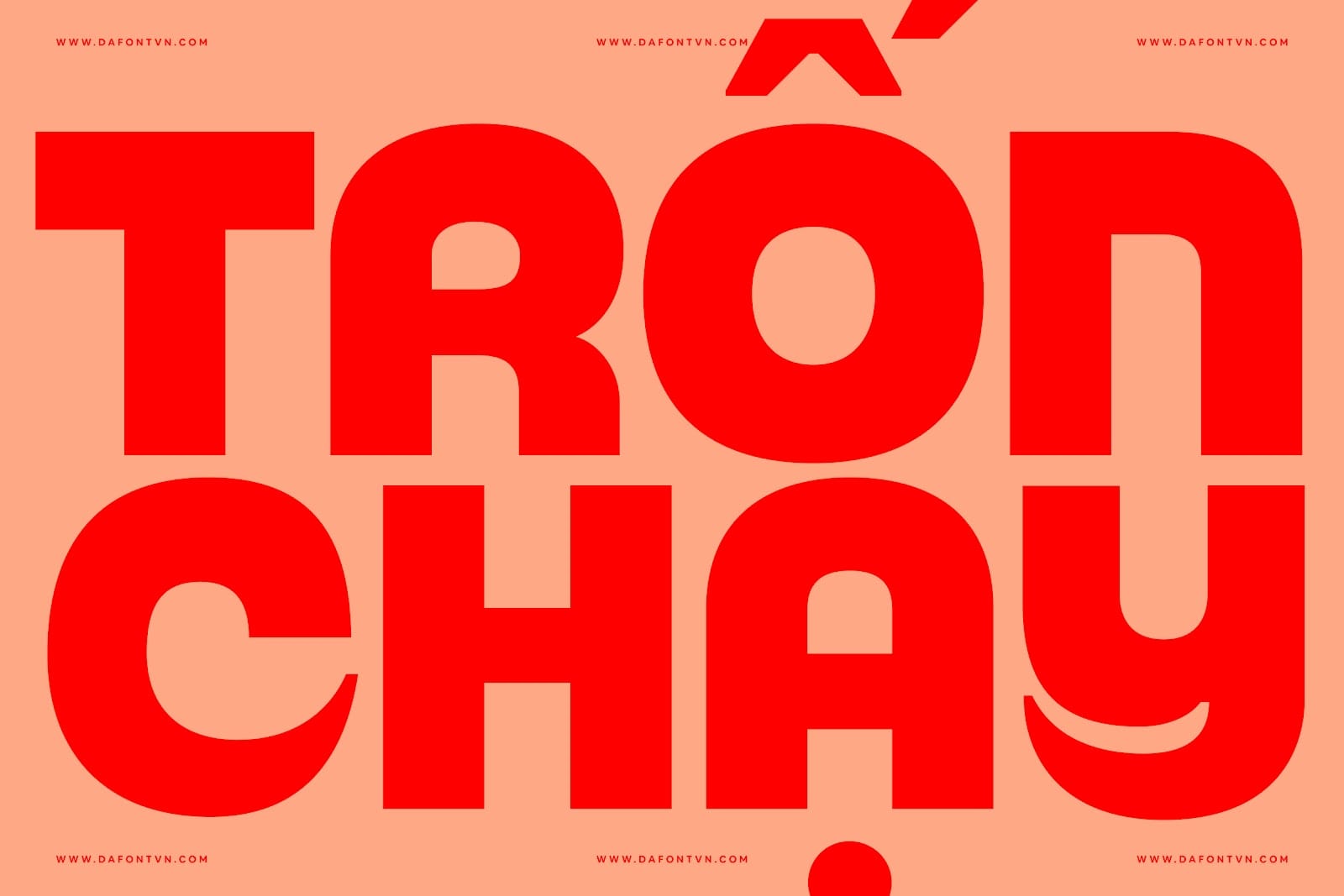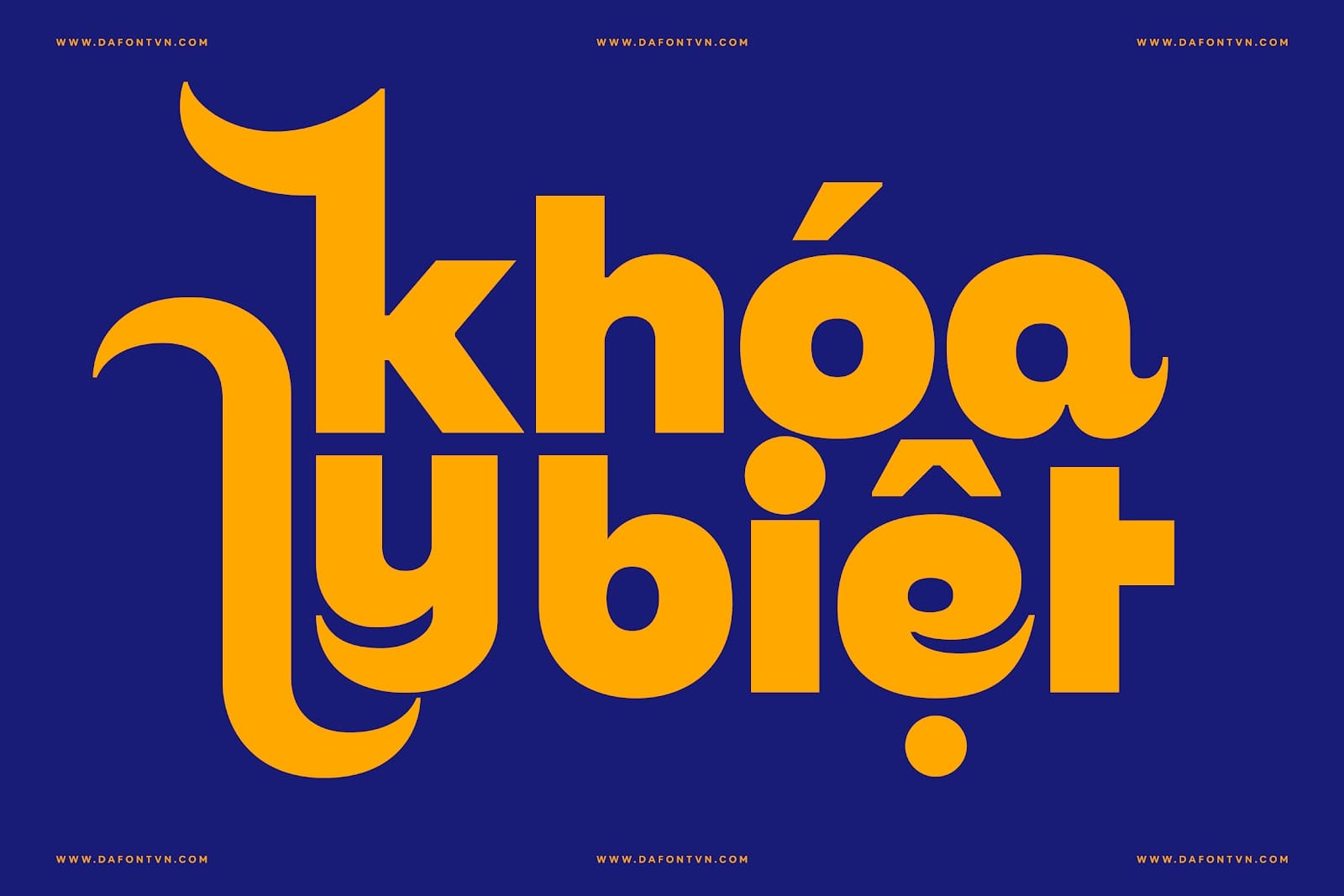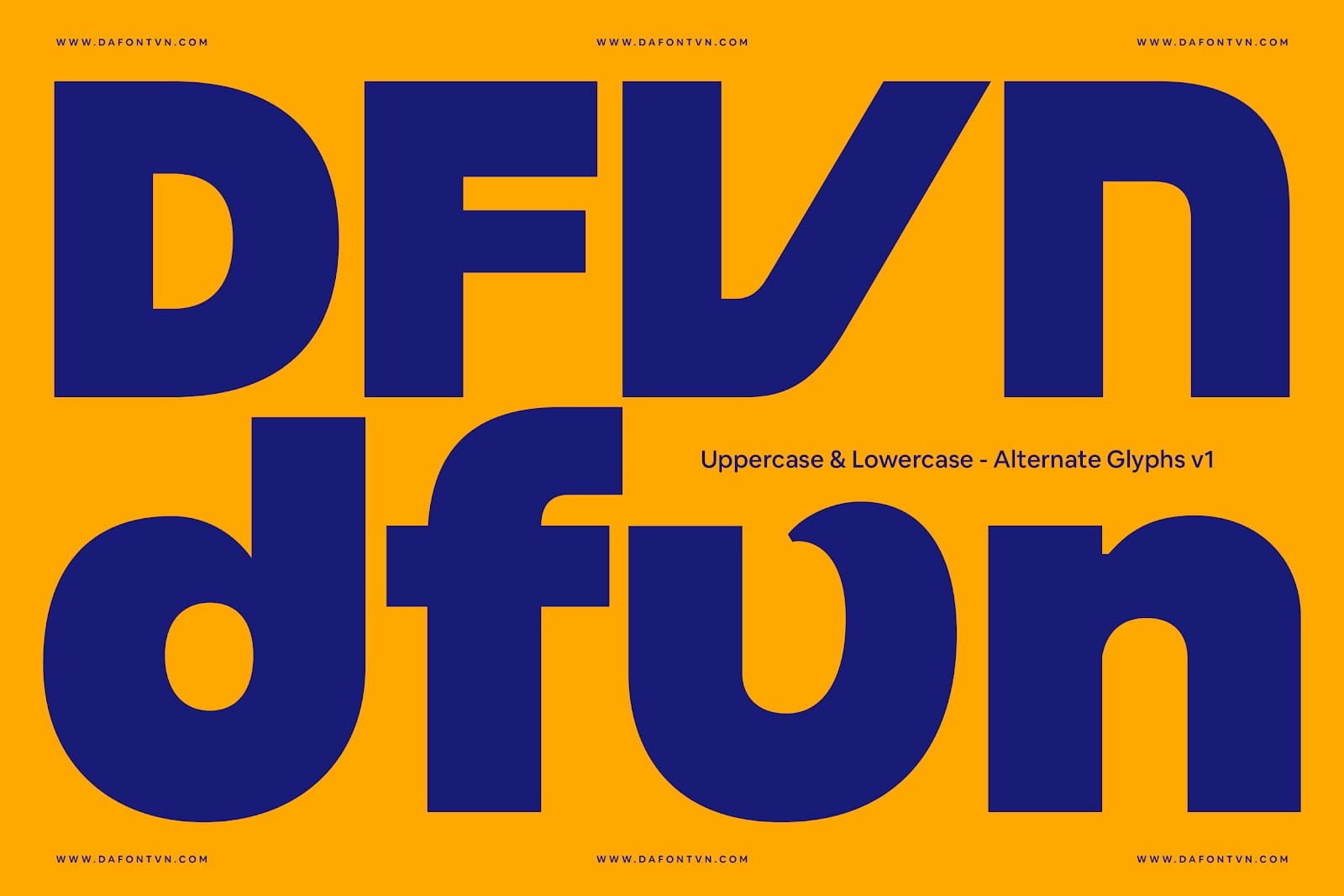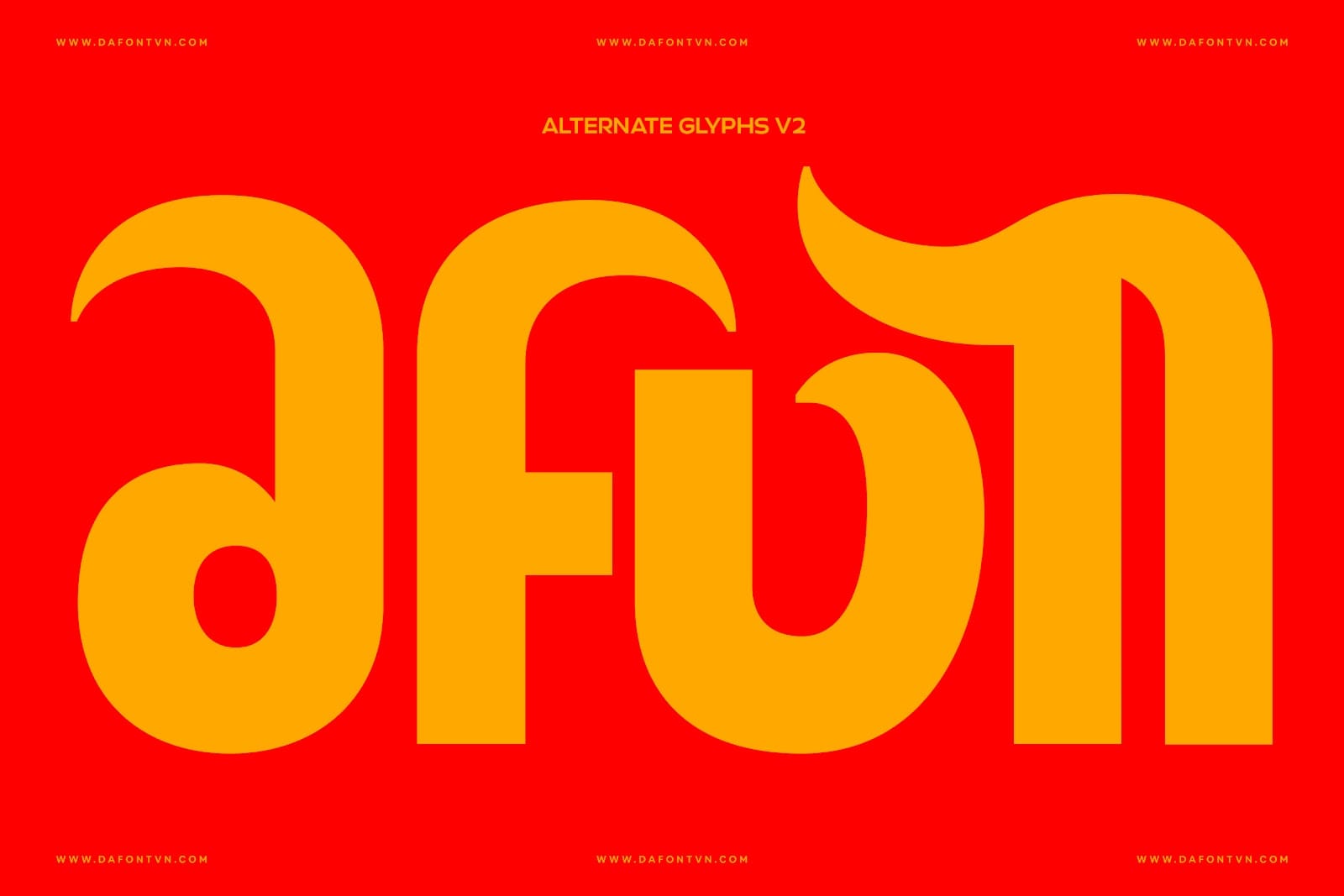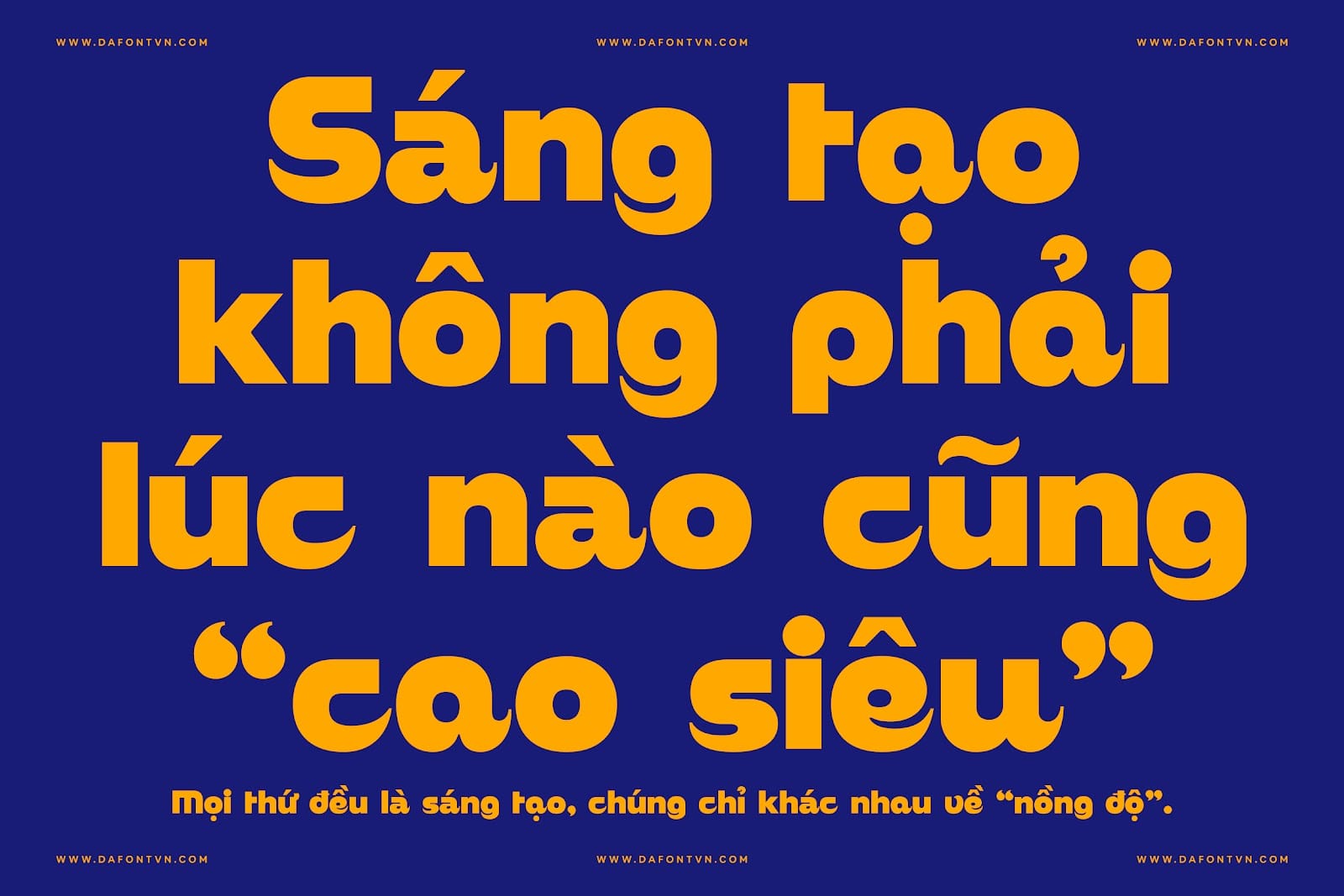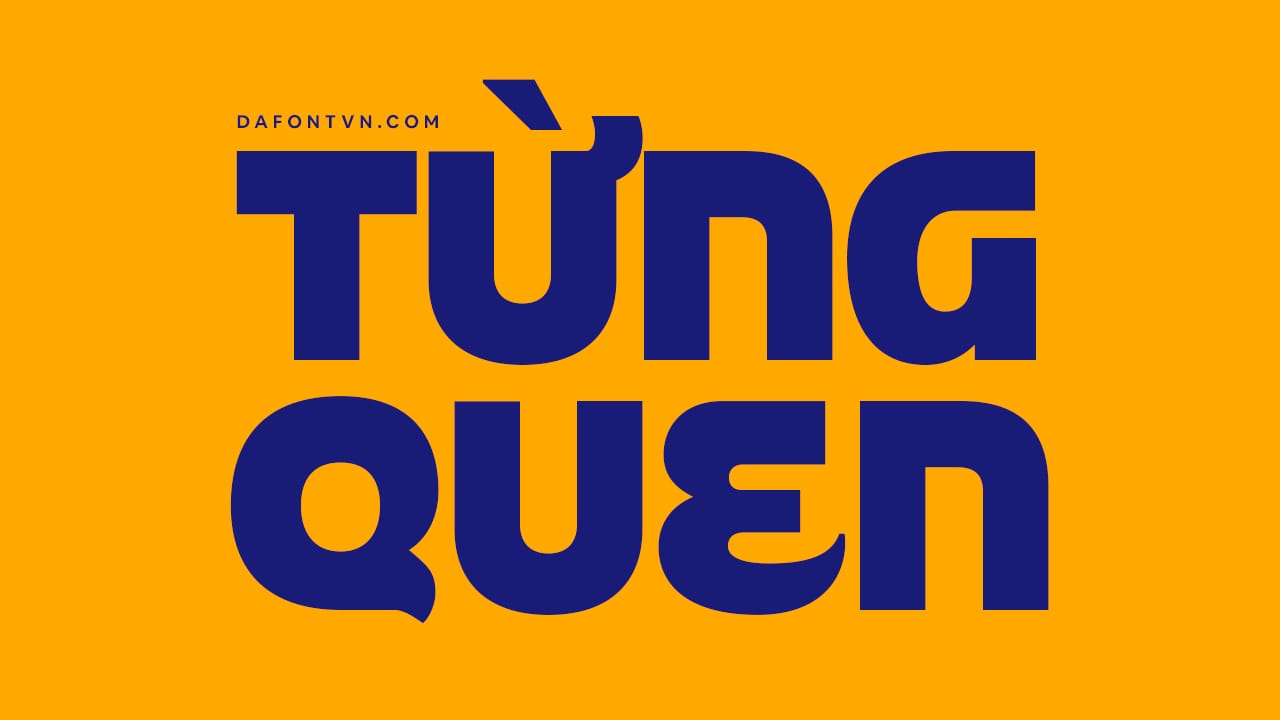
BN Equipt là một kiểu chữ sans serif siêu độc đáo chứa đầy các ký tự thay thế và được thiết kế nét đậm. Các ký tự thường và ký tự in hoa nổi bật với các nét chữ vừa vuông vức vừa mềm mại.
Font chữ này phù hợp để sử dụng làm tiêu đề, logo, tạp chí, bìa sách, typo, quotes… BN Equipt việt hóa đầy đủ, được chỉnh sửa, kerning và tối ưu để các ký tự hiển thị tốt hơn.
Ngoài ra, font có hơn 60 ký tự thay thế cực đẹp bạn có thể sử dụng bảng Glyph trên Photoshop hoặc Illustrator để kết hợp tạo ra các thiết kế độc đáo hơn nhé.